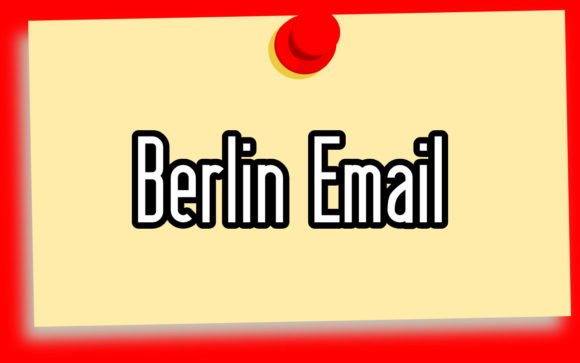
Correo electrónico de Berlín, fuente tecnológica sans serif moderna
Berlin Email es una distintiva fuente de exhibición con un aire retro-vintage. Sus estilizadas formas de letra serif/slab-serif y su diseño le dan a tu texto un carácter clásico y clásico. Con múltiples grosores y estilos disponibles (normal, negrita, seminegrita, ancha, contorno, sombra, variantes serif, etc.), esta fuente ofrece flexibilidad para diversas necesidades de diseño. Ya sea que estés creando carteles, señalización, merchandising o materiales de marca, Berlin Email ofrece un estilo tipográfico audaz y llamativo.
Por qué te encantará
Berlin Email aporta a tus proyectos un carácter fuerte y un encanto vintage, a la vez que es muy flexible y fácil de usar. Con múltiples grosores y variantes de estilo, tienes espacio para experimentar, desde encabezados llamativos y carteles llamativos hasta texto sutil para señalización o embalajes. La licencia gratuita de uso comercial (incluida con la descarga) la convierte en una opción económica para pequeñas tiendas, vendedores bajo demanda y diseñadores independientes que buscan fuentes de calidad sin gastos adicionales.
| Estilo / Vibra | Exhibición serif/slab-serif clásica, retro-vintage y audaz | Pantalla moderna y limpia, sans-serif minimalista | Expositor decorativo retro, estilizado o temático. |